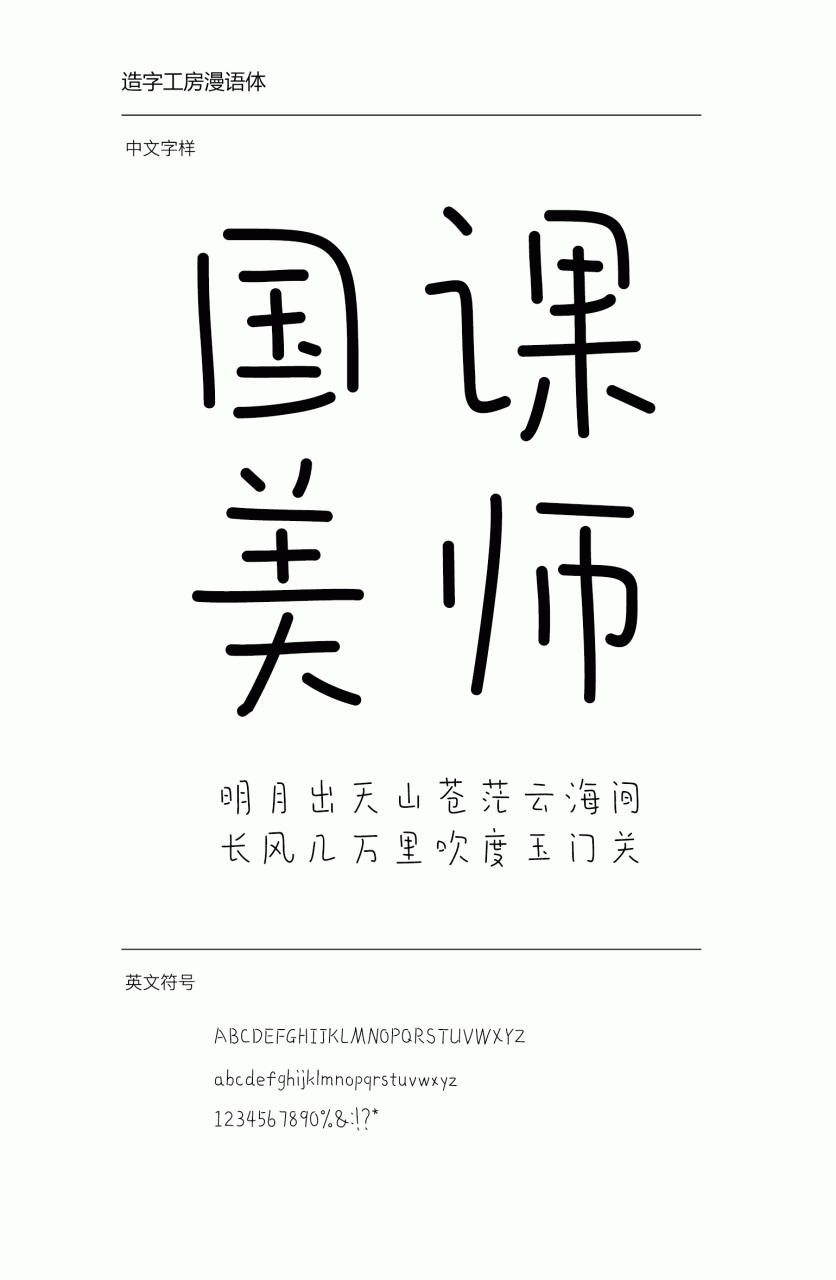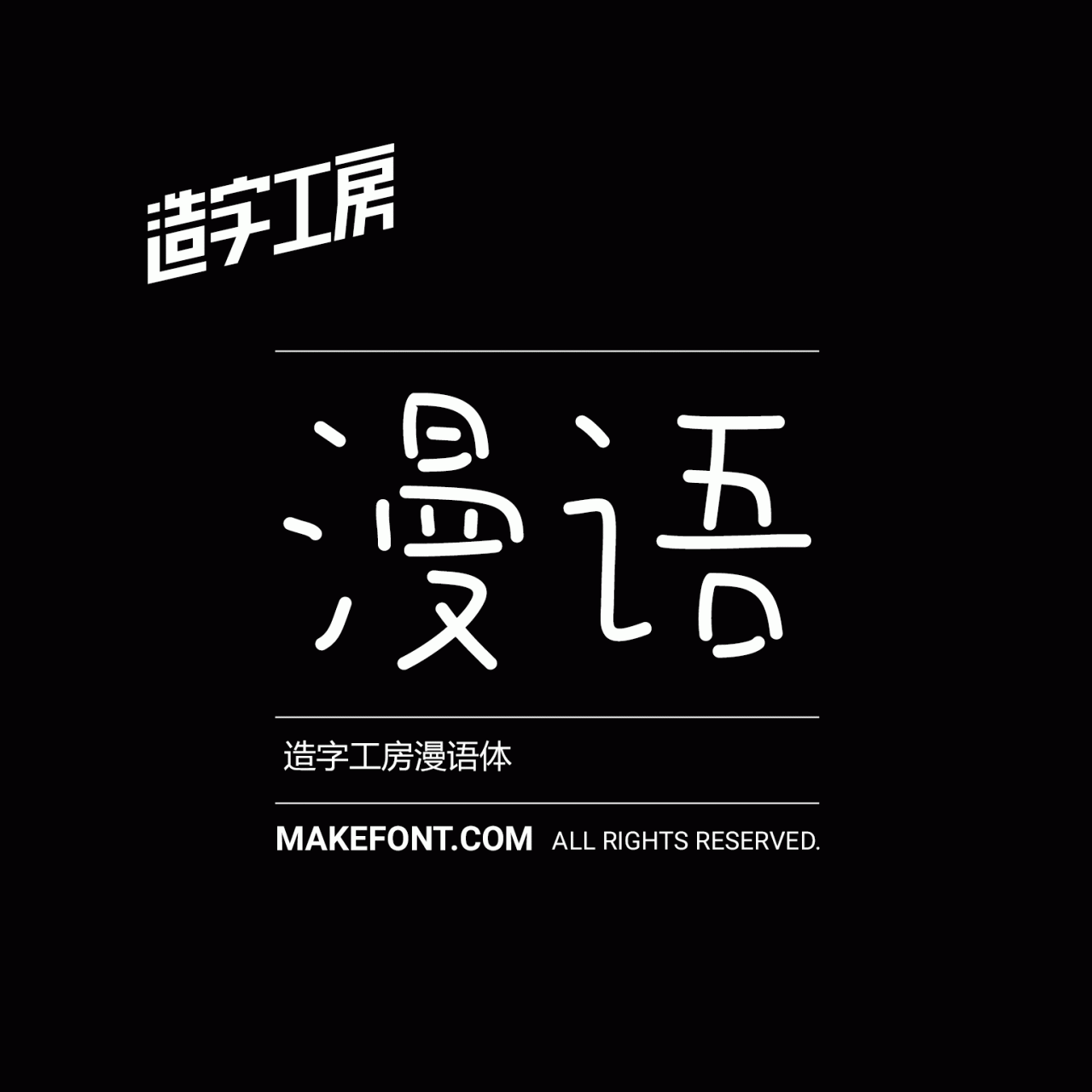
造字工房漫语常规体设计说明
造字工房漫语体结构自然洒脱,字形活泼、可爱,造型生动有趣,具有灵活的适用性。此款字体适用于儿童读物、报刊杂志标题、广告设计等视觉环境,有着极强的应用空间。本字体为简体字库,采用OpenType/CID格式,Adobe-GB1-5编码。基于中华人民共和国GB2312-80字符集标准,另按需添加101个汉字。共收容字数6864CJK汉字,ASCII常用字符100个。